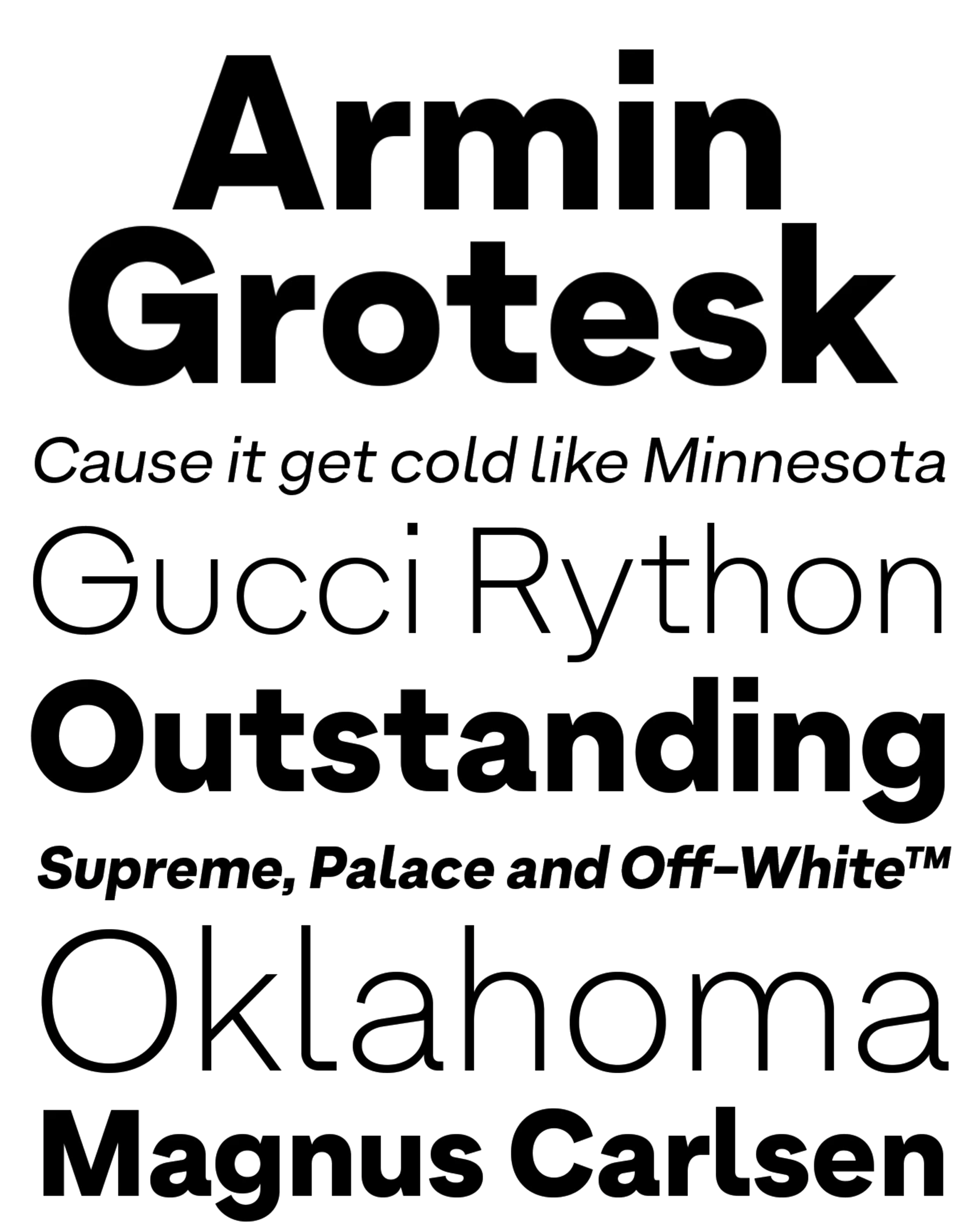
| Año | 2018 |
| Créditos | David Súid |
| Descripción | Como diseñadores gráficos, a veces es imposible no inspirarse en el Estilo Suizo, en específico en la obra de Armin Hofmann, uno de sus mejores exponentes. |
| Clasificación | Texto |
| Fundidora | W Type Foundry |